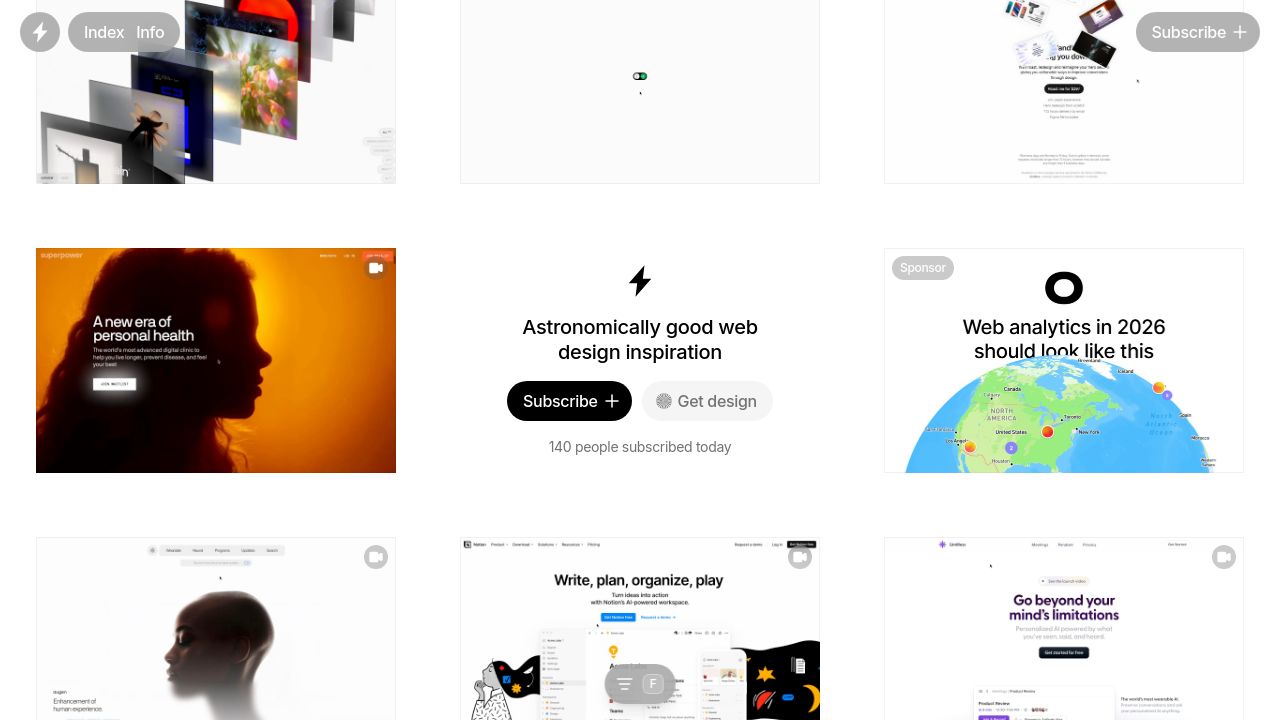
Godly.website usa Inter como fuente principal. 1 fuente detectada, última comprobación el 1 jun 2026.
Godly.website es una plataforma que ofrece una curaduría excepcional de más de 1,000 sitios web destacados en diversas áreas, como IA y Web3. Utiliza la tipografía Inter, que aporta claridad y legibilidad, lo que mejora la experiencia del usuario. Esta elección de fuente sugiere un enfoque contemporáneo en el diseño web, alineándose con su misión de inspirar a diseñadores y desarrolladores a explorar lo mejor de la web.
Godly.website usa Inter como fuente principal. 1 fuente detectada, última comprobación el 1 jun 2026.
El sitio godly.website utiliza la fuente principal Inter en su versión personalizada con un peso de 400, que proporciona una excelente legibilidad.
Inter se destaca por su legibilidad en pantallas, especialmente en dispositivos digitales, en comparación con otras fuentes sans-serif que pueden no ser tan optimizadas para web.
Inter ofrece una variedad de pesos y estilos, pero godly.website utiliza específicamente el peso 400, que es ideal para el texto principal debido a su claridad.